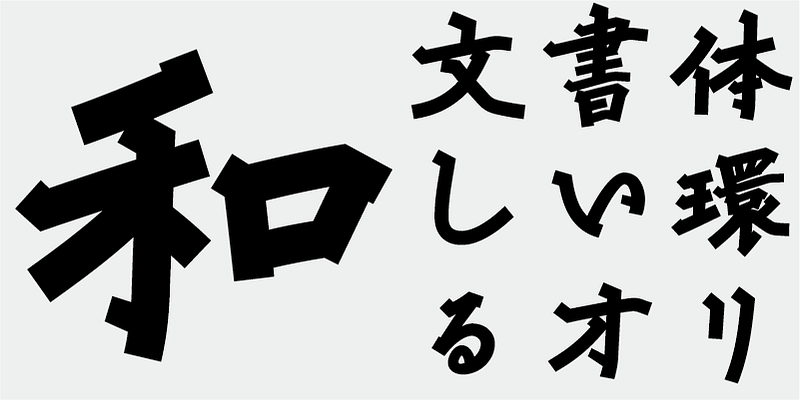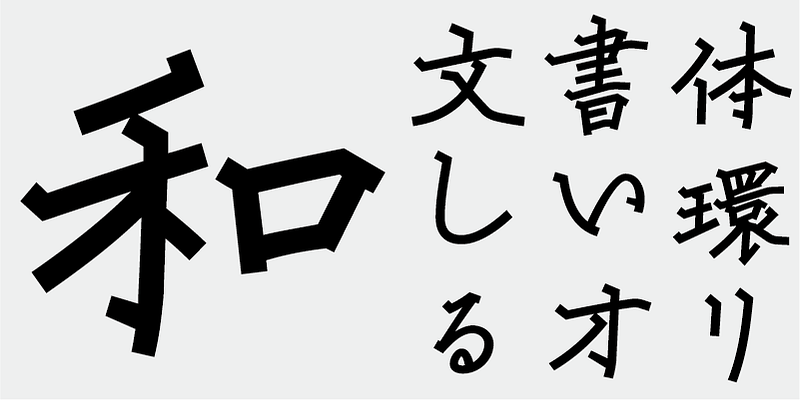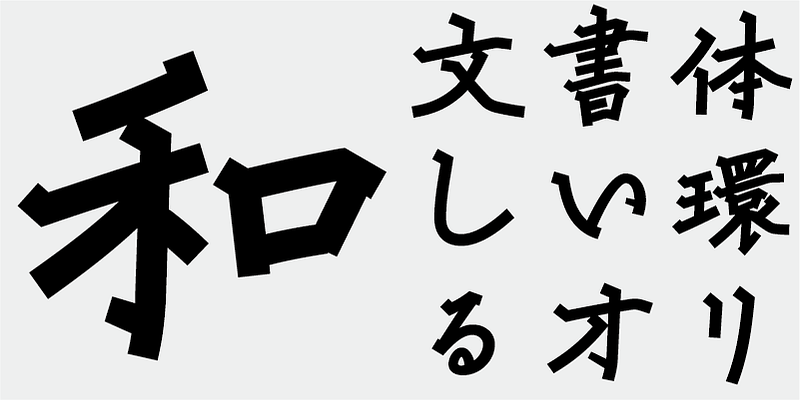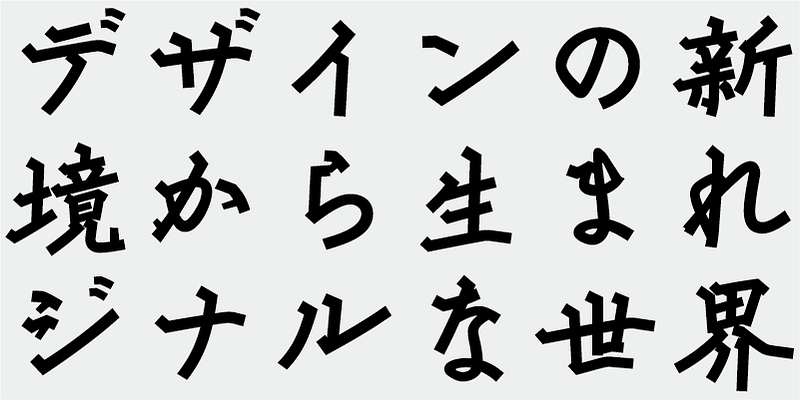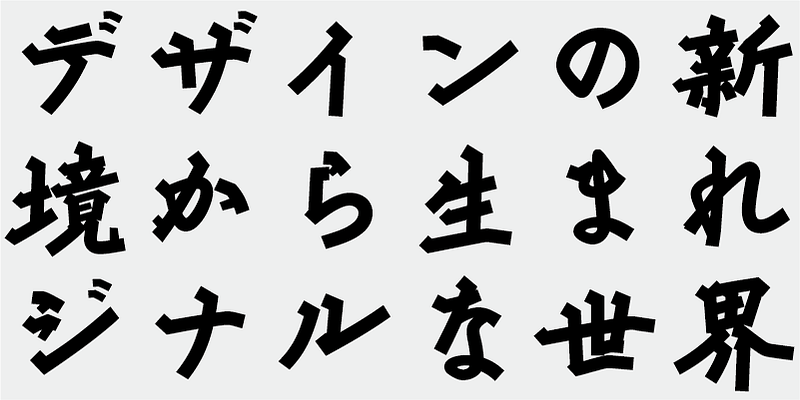
Cette police de style gothique (sans empattement) se caractérise par des structures de glyphes de style distingué et masculin. La police contient des structures linéaires délibérément conçues pour préserver une certaine douceur visuelle.
Cette police comprend les 1 000 principaux caractères kanji, choisis dans les tables de fréquence des caractères établis par les sociétés de presse, les maisons d’édition et les instituts de recherche linguistique, ainsi que 206 caractères kana et signes de ponctuation.
Dans la production de polices japonaises d’aujourd’hui, les 7 000 caractères de la norme JIS sont considérés comme essentiels. Mais toutes les polices ont-elles vraiment besoin de 7 000 caractères ? À l’ère de la phototypie, on utilisait beaucoup moins de caractères. FONT1000, un groupe de typographes indépendants, a commencé par se focaliser sur cette simple question. Nous avons sélectionné le minimum de 1 000 caractères kanji (idéographiques) nécessaires pour la composition en japonais et créé activement des polices pour les prendre en charge. Ce jeu de 1 000 caractères kanji a été créé en étudiant des données de fréquence des caractères compilées par des sociétés de presse, des maisons d’édition et des organismes de recherche linguistique, etc. Il comprend également des caractères syllabiques kana et des signes de ponctuation. FONT1000 a été créée en 2001 avec 25 designers et 25 polices de caractères. Aujourd’hui, nous avons 130 polices et comptons désormais près de 40 membres, ce qui permet de travailler sur des polices avec plus de caractères.